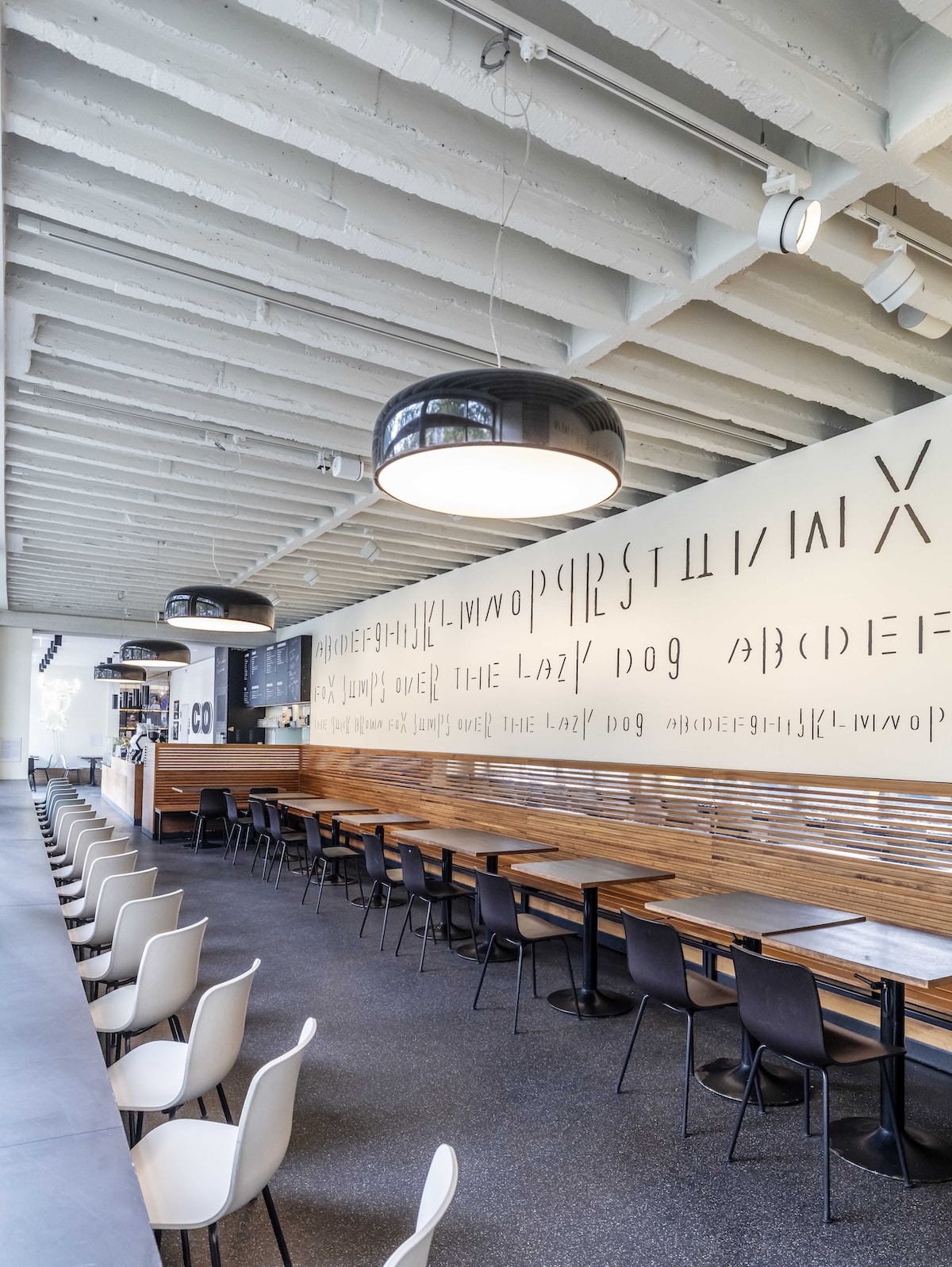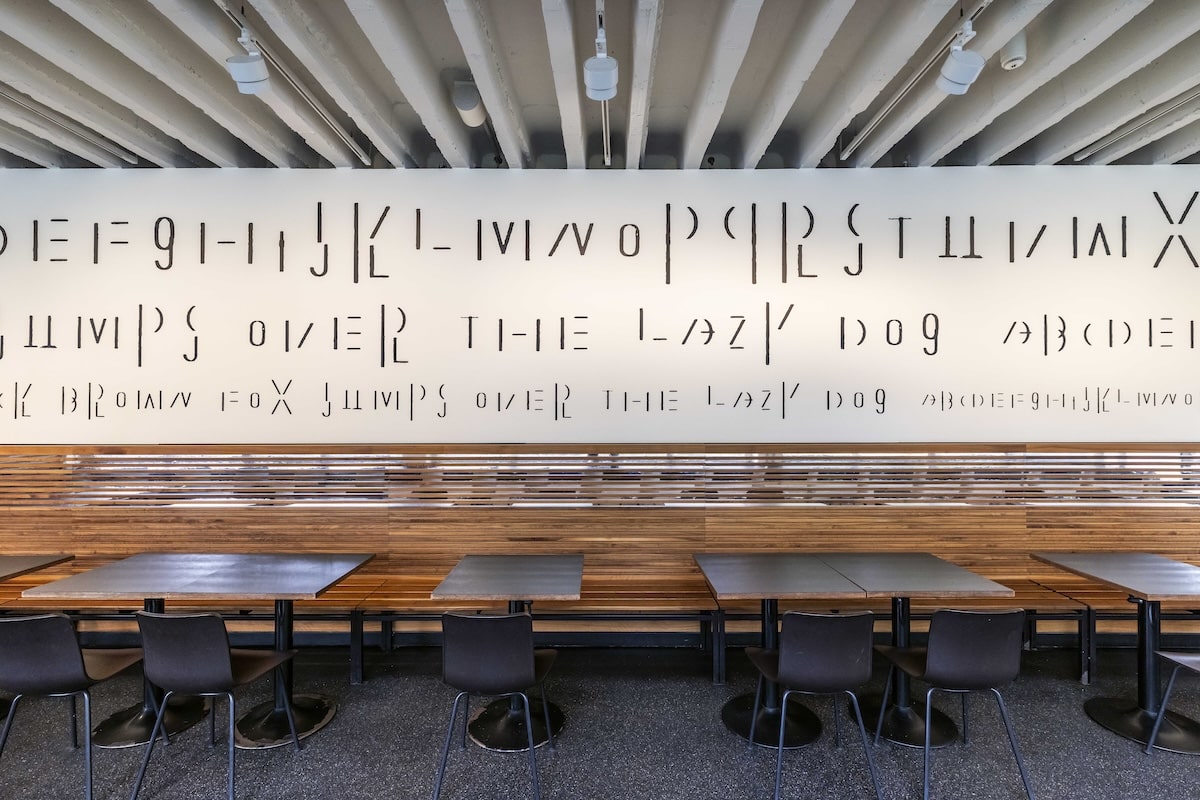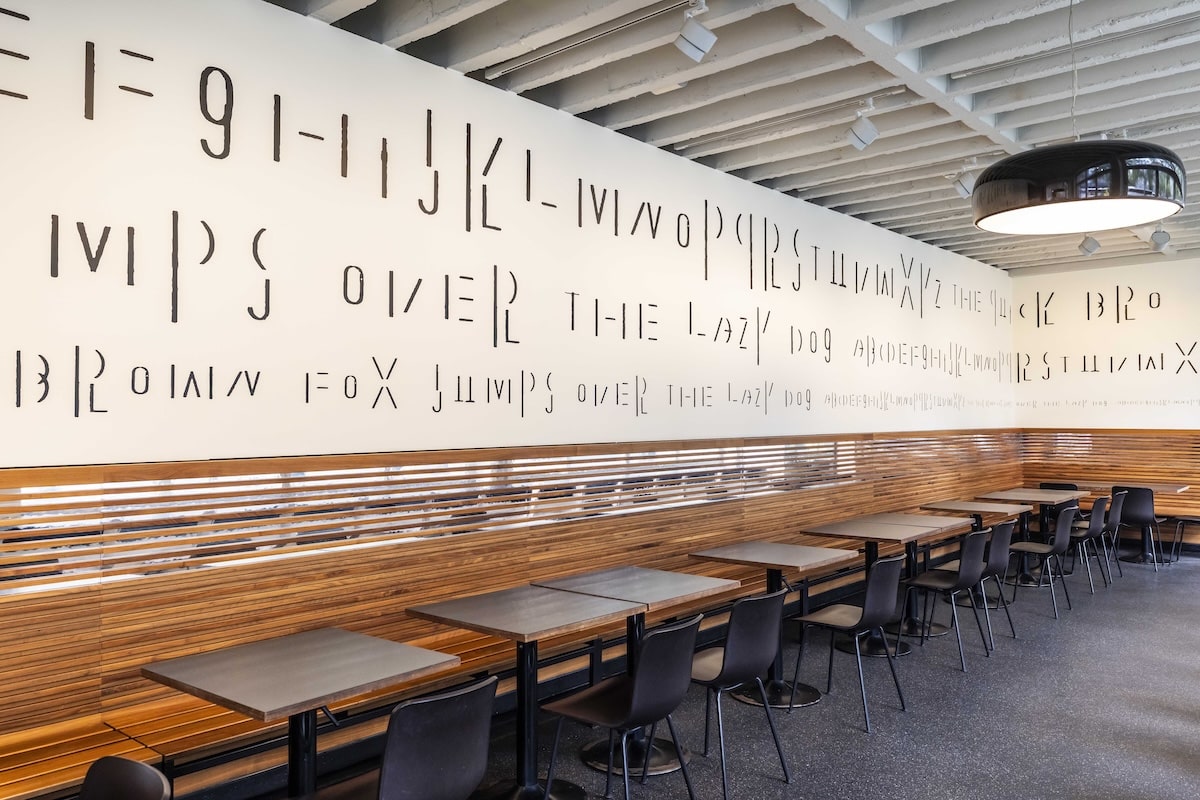
Typed Types: Beim Kaffee umgeben von Füchsen, Hunden & Typografie
The quick brown fox jumps over the lazy dog: Auf Christoph Niemann folgt jetzt im Café des Ausstellungshauses C/O Berlin eine Installation der Konzeptkünstlerin Ayşe Erkmen, die anhand des berühmten Pangramms eine ganz eigene Geschichte erzählt.
Es ist bereits das elfte Mal, dass im Café des Ausstellungshauses C/O Berlin, spezialisiert auf Fotografie und visuelle Medien, eine »Artistic Intervention« gezeigt wird.
Auf Christoph Niemann, der mit einer gewebten Illustration Bezug auf die Heliografie nahm, dem ersten Verfahren, das dauerhafte Bilder erzeugen konnte.
Auf die Jubiläumsarbeit zum 25. Geburtstag des C/O Berlin folgt im Café Bark jetzt eine Installation der Konzeptkünstlerin Ayşe Erkmen.
Ein Jahr lang werden ihre »Typed Types« den Raum bestimmen: mit einer Schrift, die aus Zeichen und Symbolen besteht, die sie auf der Schreibmaschine erzeugt hat – und die einen Satz zeigen, den jeder Gestaltende kennt.
Schrift als Bild
»The quick brown fox jumps over the lazy dog« steht dort in Vinyl-Buchstaben geschrieben, das bekannte Pangramm, das jeden Buchstaben des Alphabets enthält und von den meisten Foundrys genutzt wird, um Schriften vorzustellen.
Ayşe Erkmen hingegen, die weltweit für ihre Interventionen und Installationen bekannt ist, visualisiert den Satz auf mehrfache Weise.
Erst einmal durch ihre Schrift, die aus Buchstaben besteht, die sie auf der Schreibmaschine durch andere Buchstaben und Zeichen kreiert hat. Sie balancieren auf der Grenze zur Unlesbarkeit und werden so zum Bild.
Und zu einem, das seine eigene Geschichte erzählt. Und zwar eine, in der die Schrift immer kleiner wird, bis der sprichwörtlich faule Hund schließlich zu verschwinden scheint.
»Typed Type« hat Ayşe Erkmen (77), die in Berlin und Istanbul lebt, erstmals 2004 auf der Limerick Biennial in Irland präsentiert und wird für jeden Ausstellungsort neu konzipiert.
Die Arbeit ist bis September 2027 im Bark Café im C/O Berlin zu sehen.